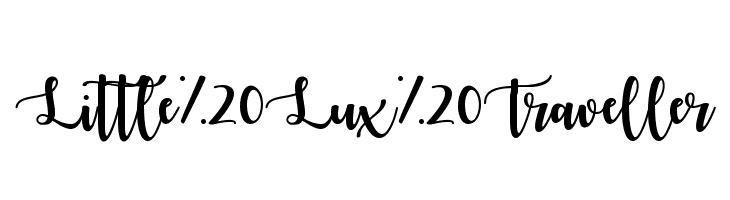
Ungewöhnliche Schreibschrift, knifflig...
Hallo liebe Schriftexperten,
die üblichen Suchprogramme (WhatTheFont & Co) versagen leider bei dieser ungewöhnlichen Schreibschrift.
Hat jemand eine Ahnung, welche Schrift dies sein könnte?
So eine ähnliche Frage hatte ich auch mal:
@Schnitzel hatte mir damals zwei Links gepostet mit solchen Script-Fonts. Vielleicht ist ja was dabei :-?:
Edit: Die kostenlose Bromello tut es auch (auch wenn sie nicht ganz dem Beispiel entspricht): http://www.ffonts.net/bromello.font?text=Little Luxe Traveller
Ich habe zwar die genaue Schrift noch nicht gefunden, aber noch gebe ich nicht auf. ;-)
Bromello ist auch klasse!
Autumn in November. Free for personal use.
How to:
– Suchbild runterladen
– Kontrast erhöhen
– ungefährer Anschluss Buchstaben suchen (cyan markiert)
– Schriftzug in Einzelbuchstaben zerlegen
– Speichern und whatfontis.com zum Fraß vorwerfen
– Dort ist’s der Treffer Nr. 13
Hat insgesamt 2 Minuten gedauert.